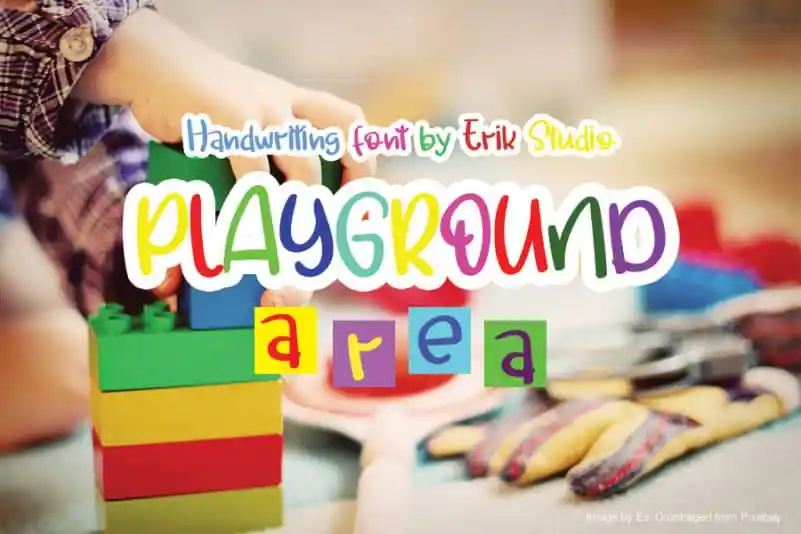
Playground Display Font – Fonte Grátis
Playground Display Font
A Playground Display Font é uma fonte serifada inspirada na caligrafia que se move ao longo do nível base, criando uma sensação de dança e elegância. Esta escolha de fonte romântica e alegre é perfeita para criar cartões de aniversário, convites de casamento ou qualquer outro projeto design que precise adicionar um toque romântico e pessoal ao seu trabalho. Com linhas delicadas e alegres, esta fonte dá vida aos seus designs, oferecendo uma maneira criativa de expressar amor e personalidade em cada palavra escrita. A Playground Display Font é ideal para quem busca imprimir um pouco mais de sensibilidade e charme em seus projetos gráficos.